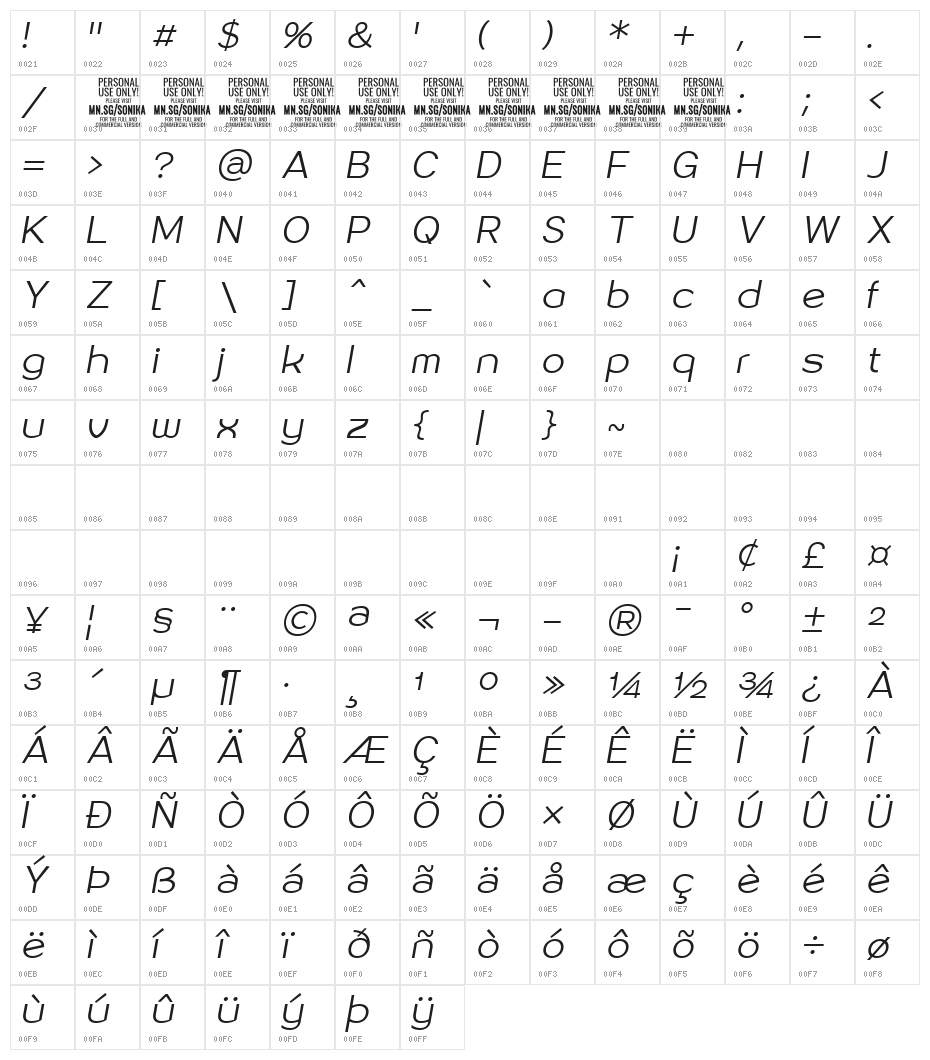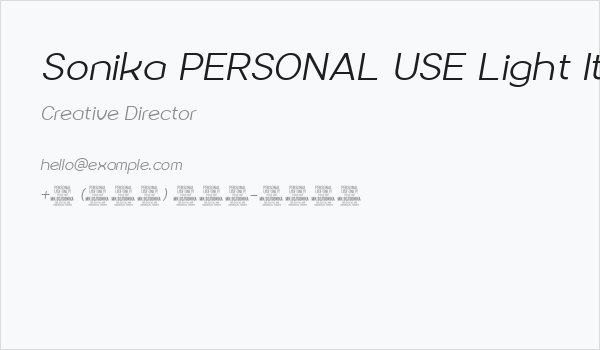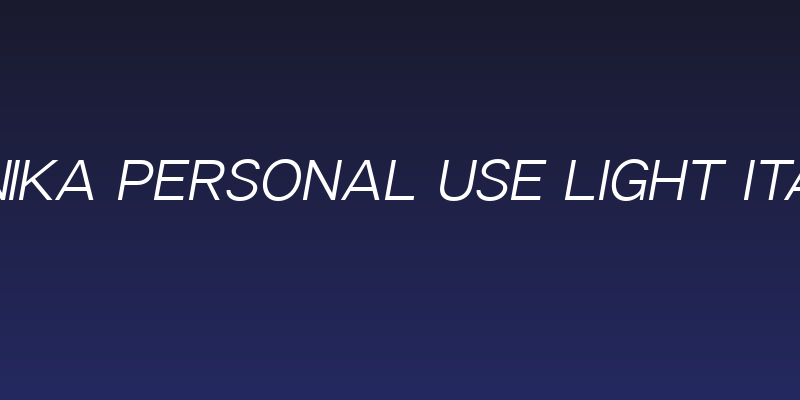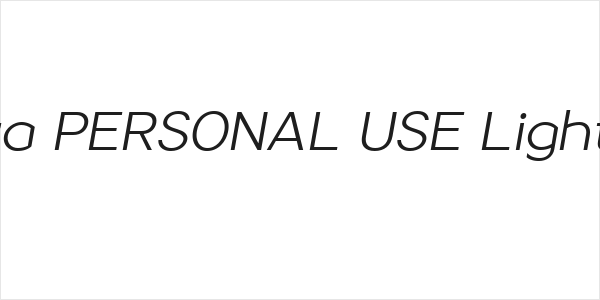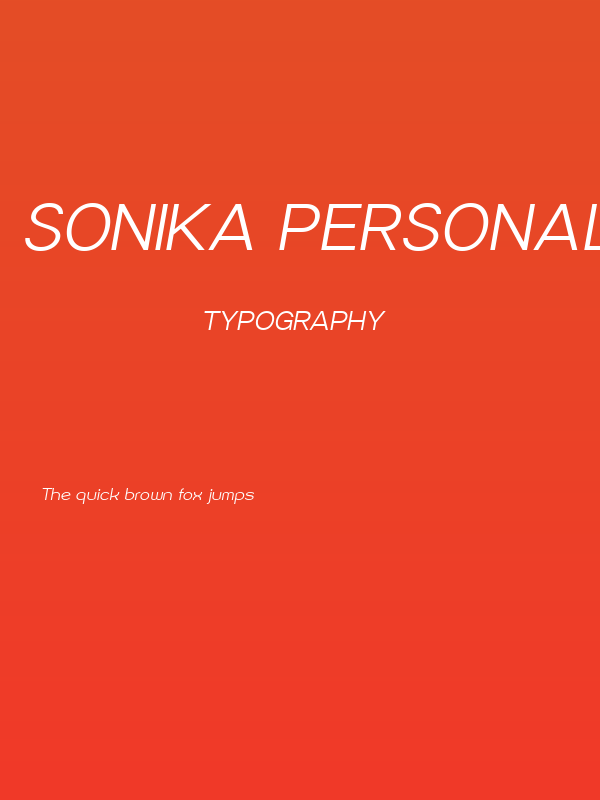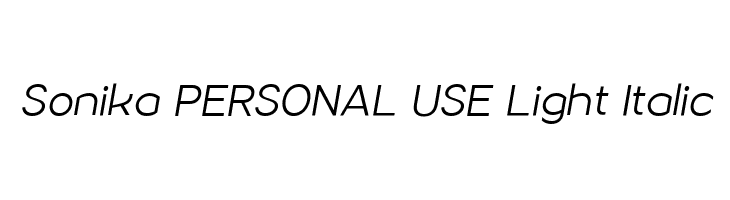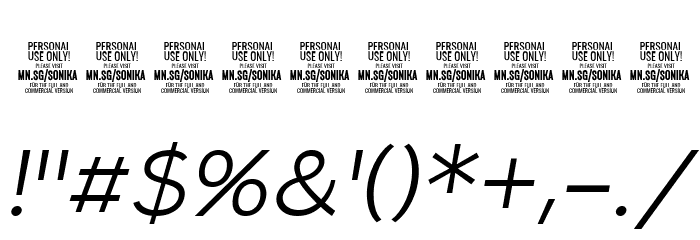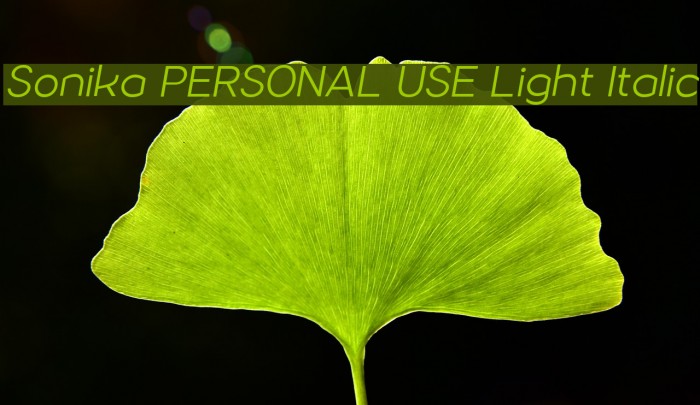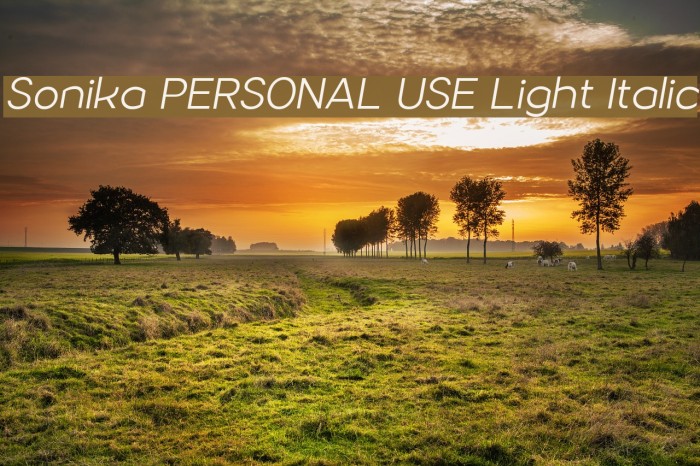
Sonika PERSONAL USE Light Italic Font
✎ Modern
| Kategorien | Modern |
| Anwendungsfall | Headlines, Body text, Logos |
| Vorgeschlagene Projekte | Ideal for branding, fashion magazines, modern websites, and elegant invitations. |